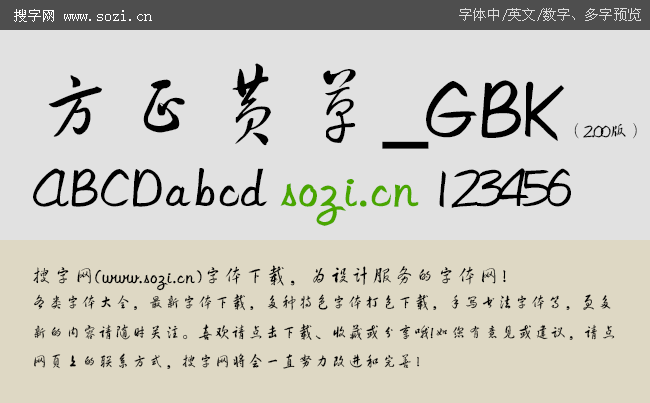
方正黃草_GBK
搜字網(wǎng)提供一款方正黃草_GBK中文字體下載,方正黃草是一款手寫風(fēng)格的書法字體,該字體書寫流暢,瀟灑大方,整體效果十分出色,GBK碼包含字體更全,適合應(yīng)用于廣告設(shè)計(jì)、名片設(shè)計(jì)、包裝印刷、兒童產(chǎn)品設(shè)計(jì)等應(yīng)用。